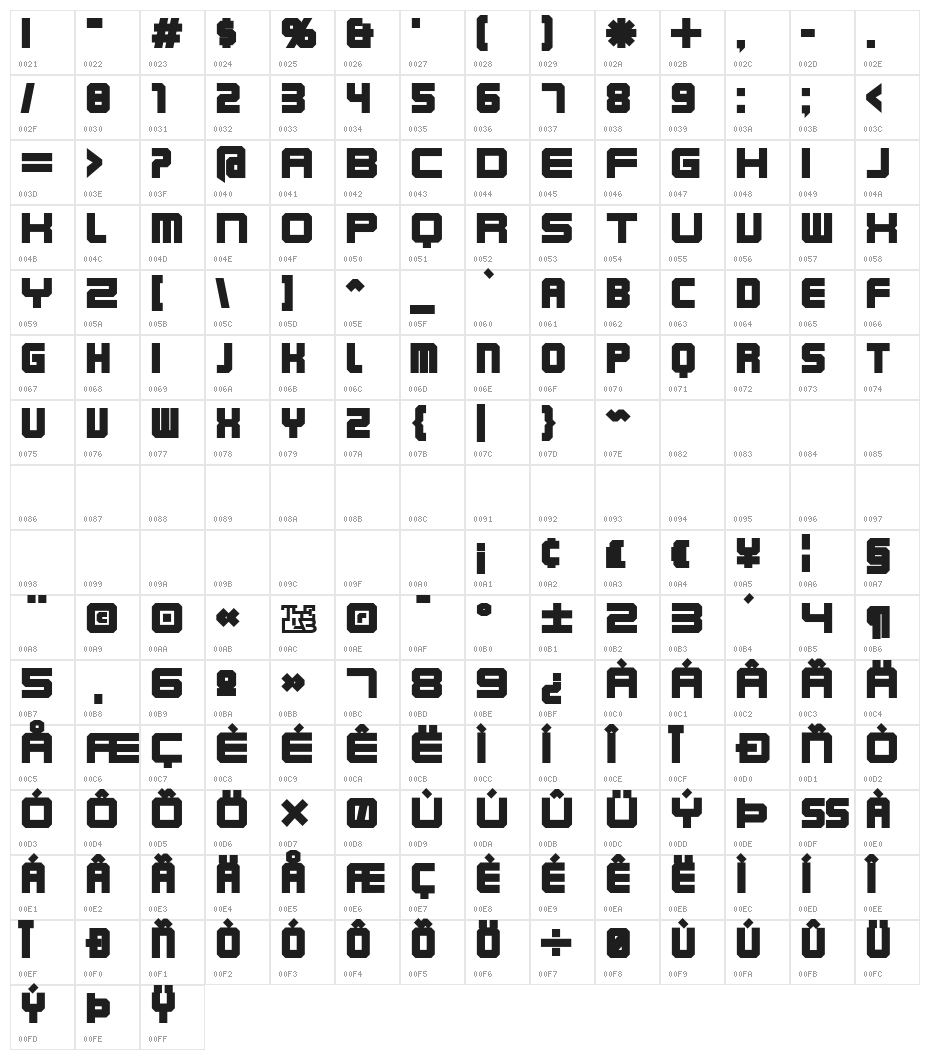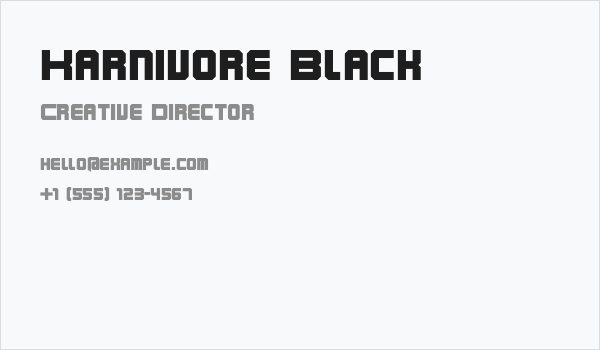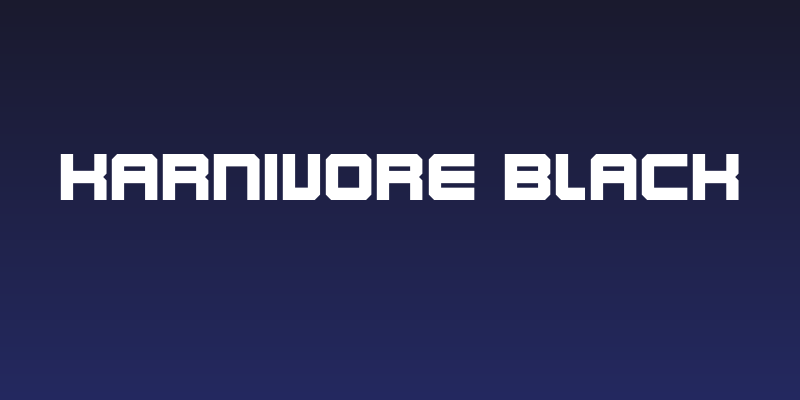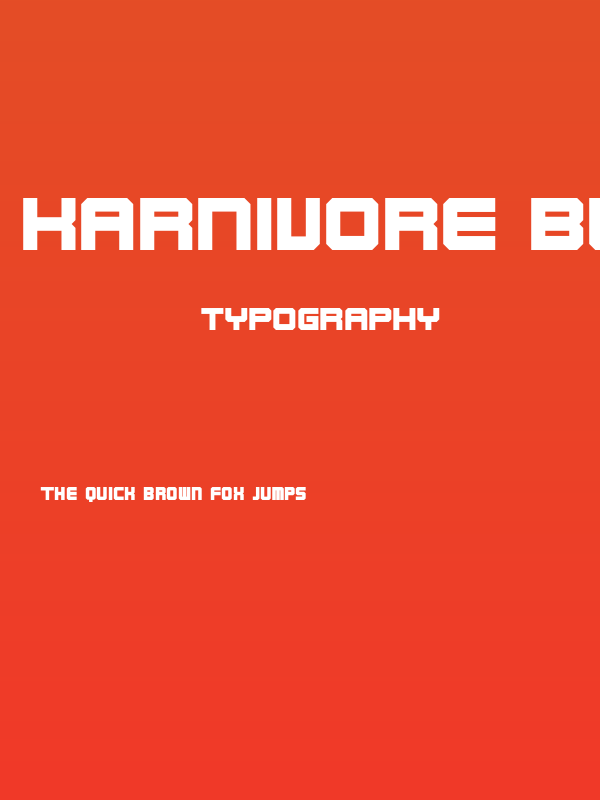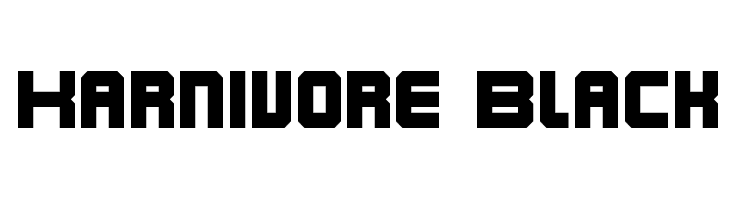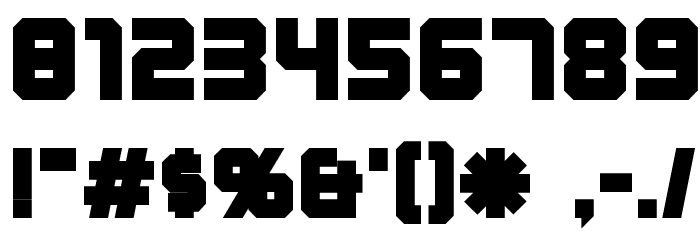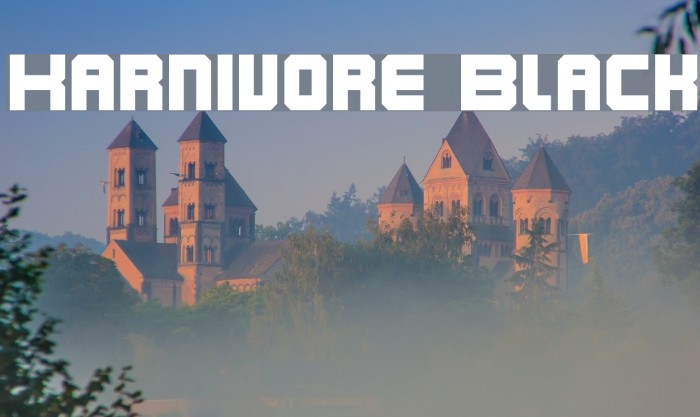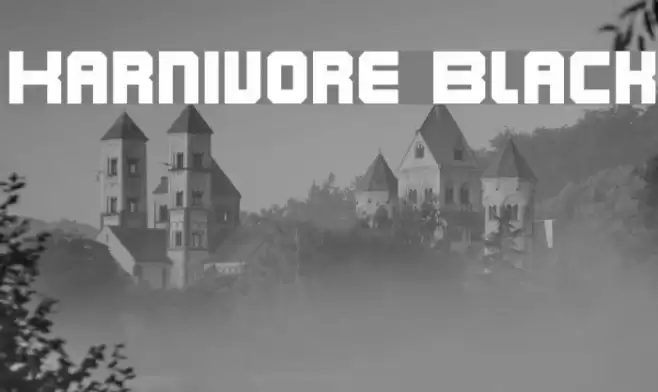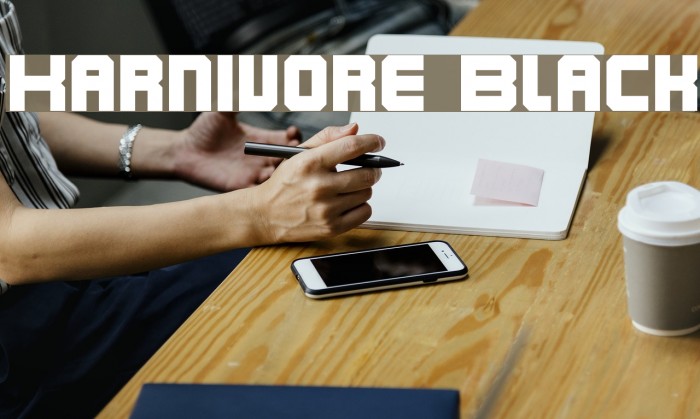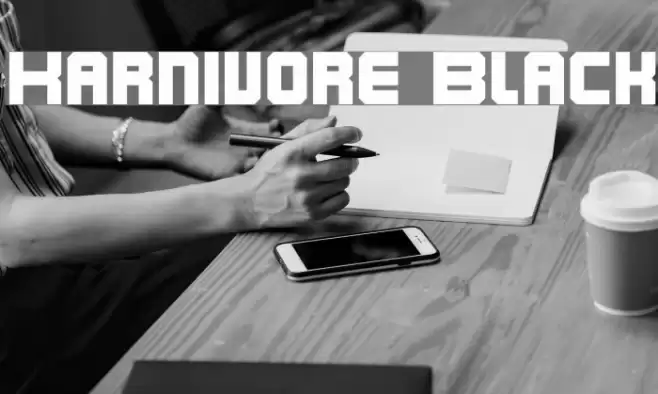
Karnivore Black Font
✎ Thick
Fonts by Apostrophic Lab
| Proyectos propuestos | Ideal for posters, logos, video game graphics, and branding that requires a strong, impactful look. |